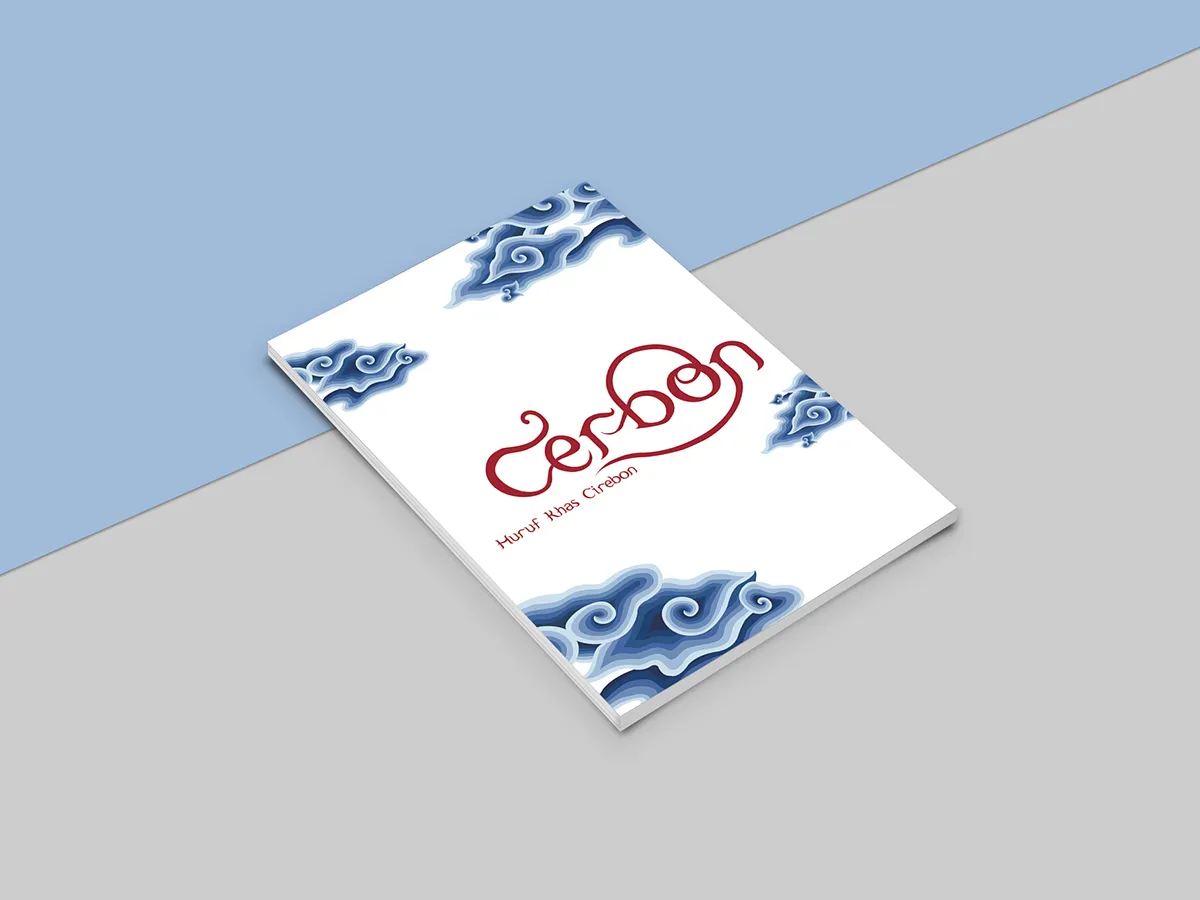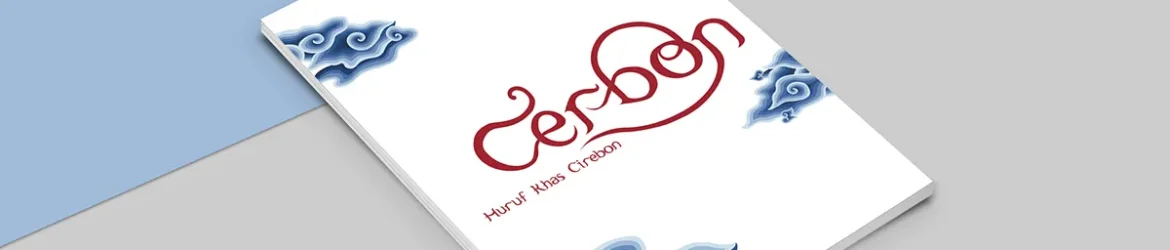
A Cerbon Typeface : Indonesian Heritage é uma fonte de linhas finas e elegantes ideal para aplicativos que buscam incorporar a rica cultura indonésia na sua interface. Desenvolvida pelo designer Hamilton, esta fonte não apenas traz um toque autêntico à sua identidade visual, mas também valoriza a diversidade cultural do país. Seu design minimalista e fluido combina bem com textos de diferentes tamanhos e tipos de conteúdo, desde websites até cartões de visita personalizados. Ideal para marcas que valorizam o legado indonésio, esta fonte é uma excelente escolha para aqueles buscando incorporar a cultura e história do país em seus projetos digitais. Com seu design moderno e sem ser excessivamente ornamental, Cerbon Typeface : Indonesian Heritage é perfeita tanto para um ambiente de trabalho formal quanto para ambientes mais relaxados.